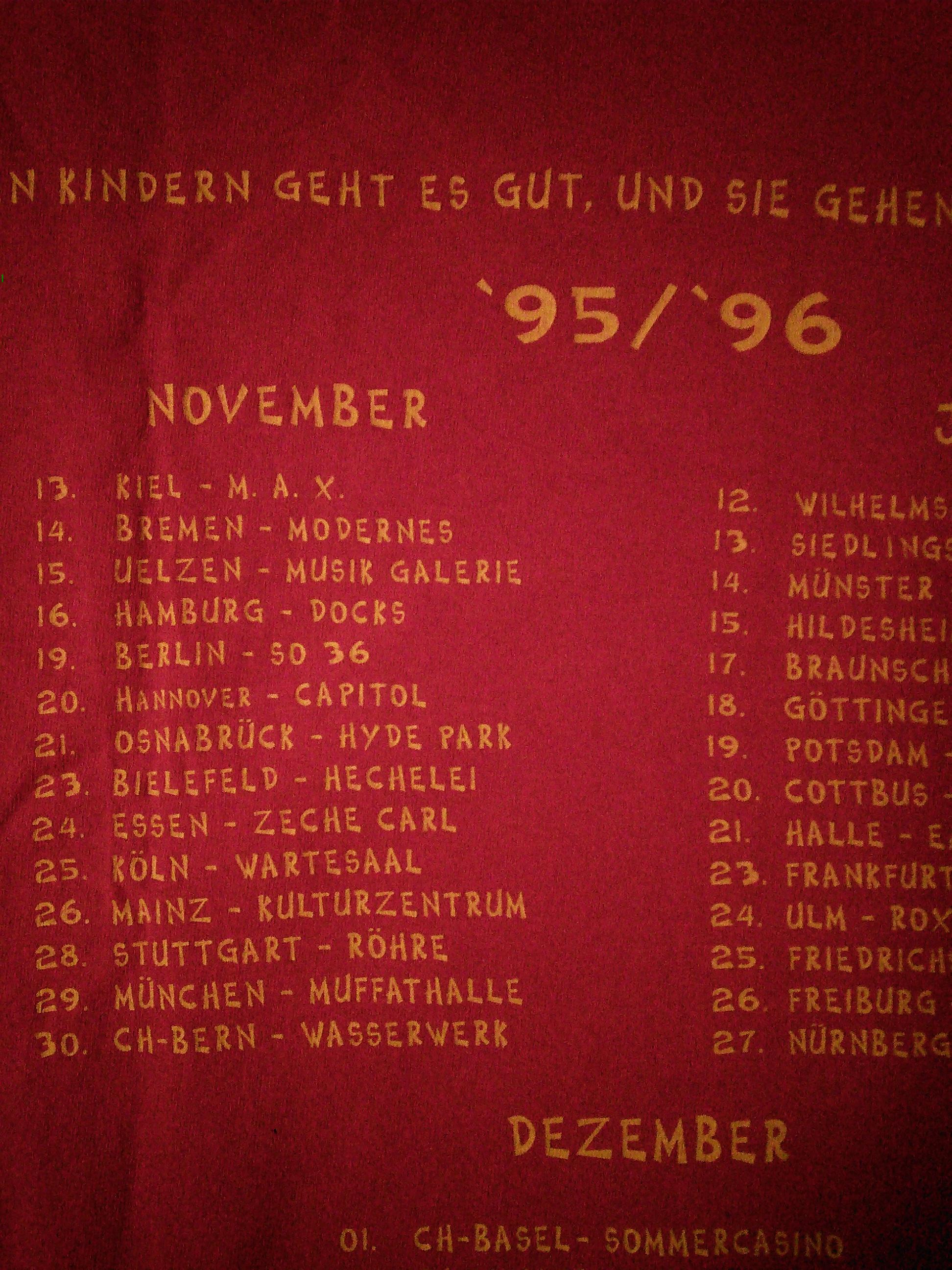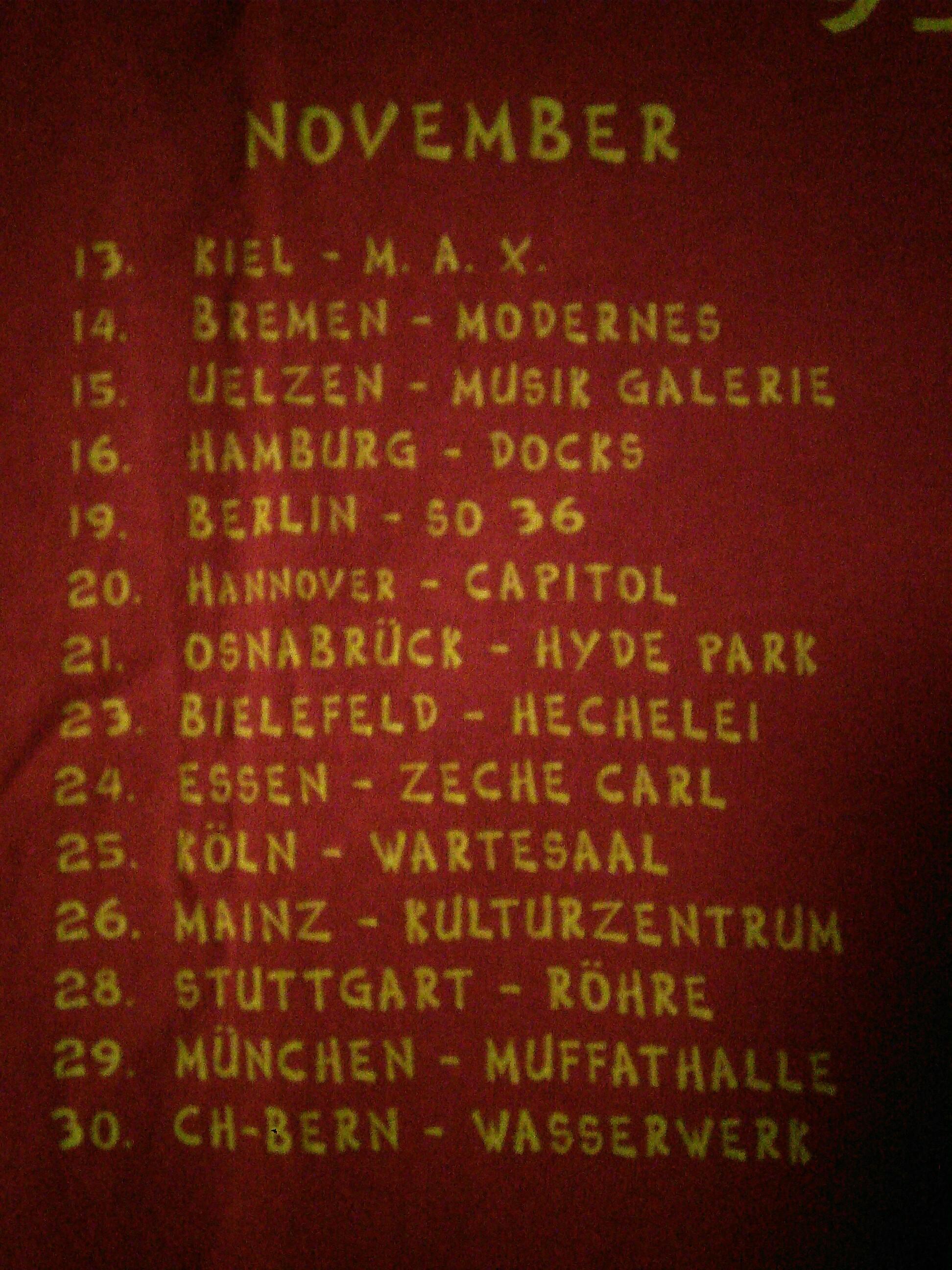
Schrift vom Tourshirt
Von diesem Tourshirt suche ich die verwendete Schrift.
Es ist aus dem Jahr 1995.
Gelöst von RobertMichael
Ein Fall für das alte Corelbuch! Und durch Zufall gleich die richtige Seite aufgeschlagen:
Seite 17: Cosmic Two — schrecklicher Font, bitte nicht wiederverwenden, jedenfalls nicht für so lange Texte.
Ich glaube mein Corelbuch ist von der 6er Version, ich habe den Font jetzt nicht by Myfonts gefunden, vermute aber das dieser auch noch unter anderem Namen veröffentlicht wurde. Bei Corel steht das meistens in der Klammer hinter dem Namen, hier jedoch nicht.
Die Cosmic Two war definitiv bei Corel Draw 6 dabei, Copyright ist: © 1992 Corel Corporation. Bei Version 3 war die Schrift noch nicht dabei, ebenso nicht in Version 11. Lt. Schriftlisten von Ulrich Stiehl war sie aber in den Versionen 4, 5 und 9 enthalten und so wahrscheinlich auch in den Versionen dazwischen.